人们说“字如其人”,意思是从一个人书写的字体当中就可以看出书写者的性格特征来。一个人如此,一个国家、一个民族亦然。那么什么字体最能代表华夏民族的性格特征呢?笔者认为是宋体字。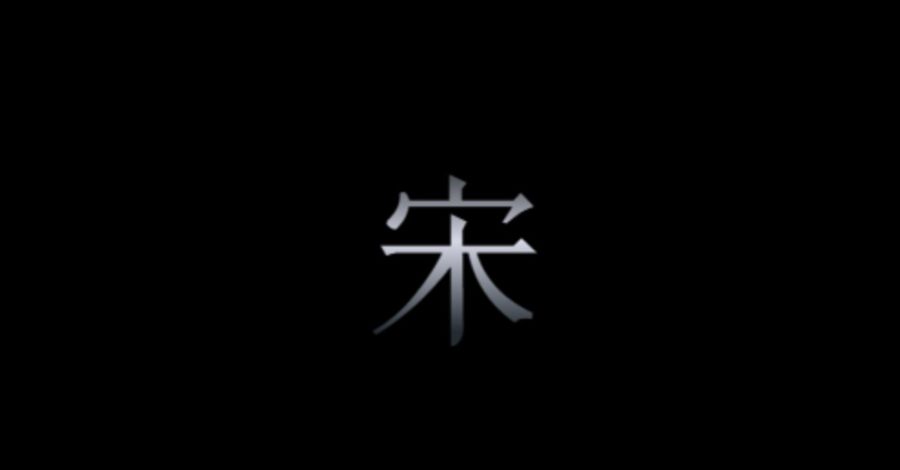
中国汉字及书法的演变大致是这样的一个过程:甲骨文、金文、大篆、小篆、隶书、草书、楷书至仿宋体、宋体字,这一过程体现了人类追求简约明朗、均衡对称、整齐统一的、程式化的总体趋向。
公元前221年,秦始皇建立了中国历史上第一个统一的中央集权制国家,随即采纳丞相李斯“书同文” 的建议,改大篆为小篆。这该是秦始皇最为智慧的一举,因为通过武力只是在地域上统一了中国,而“书同文”的统一,实是在文化上统一了中华民族,使得中央帝国在秦以后,无论战争不断、异族统治、分分合合,都只是朝代更迭而已,最后都是在汉字的伟大旗帜下繁衍、发展、壮大。到了汉代,中央集权制得到了进一步的发展和加强。这时小篆又逐渐简化演变成为隶书,史称“隶变”。在这一变化中,汉字的书写工具起了决定性的作用,毛笔的书写方式对篆书进行了方正平直化的变革,使图画性质的汉字转向抽象化,并初步形成了汉字的笔画及结构特征。独特的书写工具也成就了中国书法,柔软而富有弹性的毛笔,能随意地弯曲扭动,潇洒自如地表现出各种粗细、大小、曲直、刚柔的线条变化,更能把书者的情感赋予其中。这种“软笔”可横、可竖、可点、可捺,形成了中国书法特有的形式风格和文化特征。书者的技艺到一种高度时,毛笔在手,字已非字,点、画、线条随心书写,千变万化,以至所书之字似有生命的境界。从汉以后,中国书法稳步发展,到唐代正楷字体已达到程式化的顶峰,也为雕版印刷做好了准备。顶峰面临的是什么?是下坡,还是重新开始?唐楷成了宋体字的起始点。楷,模范也,因此,楷书顺理成章地成了中国雕版印刷字的楷模。
雕版印刷术是我国的四大发明之一,其历史可上溯至隋唐。早期雕版印刷刻写的字体,常由书法家撰写楷书后由刻工们直接反拓后临刻。刻工们对书法家十分敬重,所刻字体都尽可能地保存了书法的特点,因而有着浓厚的书法味道。这种字就是我们今天所说的“仿宋体”,也是“宋体字”前身。因此,宋体字的演变过程是通过雕版印刷技术,从书法正楷到仿宋体,再到宋体的。但为什么产生于唐宋先于宋体字的仿宋体,会叫仿宋呢?原来,这是在我国进入铅活字印刷时的事情。1916年,我国著名的书法家、篆刻家丁辅之和丁善之两兄弟参考北宋古刻善本仿写制作了仿宋体字,当时命名为“聚珍仿宋”。
由于社会对书籍需求的增长,刻工又必须更快、更多、更好地完成任务。因此,他们直接对唐代三大书法家的楷书进行改造加工,在用最少刀工的条件下,刻写出楷书的特征,这就形成了我们今天所说的宋体字。宋体字产生于唐宋,但成熟于明,所以在东邻日本称之为“明朝体”。可以说,宋体字是与中国书法一脉相承的,是对中国书法楷书的终端释义。宋体字在笔画上保持了中国书法的特点,它对书法运笔进行了高度的艺术化概括,并非常巧妙地、合理地把中国书法楷书的特征用刻刀及传统印刷术的形式反映出来,得到了中华民族的认同。
在品味和设计宋体字时,对中国书法和木版刀味、雕版印刷痕迹韵味的追求是十分重要的。如果没有这种感觉,那只是美术字而已,现在的圆体、综艺体就根本没有传统书法的味道。
今天,版本学家对宋体字下的定义是:“横平竖直,横细竖粗,起落笔有棱有角,字形方正,笔画硬挺。”起落笔的棱角,是宋体字一大特征,是雕版刻工们在长期的刻写过程中对唐楷笔画归纳化处理后形成特有的装饰化特征,是刻刀留下的韵味,它既保留了楷体的本质特点,又比唐楷更加方正有力。这种刀刻的痕迹在传统印刷的过程中,因印墨和中国纸张的因素,再加上压力,使得最后印制的效果,其字的棱角又稍稍圆润浑厚起来,十分耐看。因此,学书法要上溯秦汉,而设计宋体字却要直追唐楷和宋明的雕版印刷味、刻刀味,这是宋体字的源头。
在有形的中国文化中,千百年来一直在使用的首推宋体字。宋体字的形态特征和文化特征也在无形之中影响了一代又一代的中国人。中国人从小在一个个小方格、大方格本中练习写字,老师要求要根据字体的笔画顺序把字端正、均匀、居中地写在方格内,不能偏格也不能逾越方格,要在这方格内经营笔画的位置,相互谦让,安排好每笔每画,利用好每个小空间。正是这些因素,养成了中国人做事规矩守信又善于经营位置的国民性格。
如今学术界把宋体字排除在中国书法之外,当成美术字,这是非常不对的,书法可将金石纳入,为什么不可以将雕版纳入。因此,要正本清源地指出:宋体字不是美术字,它是正本汉字。美术字是对正本汉字进行美化、装饰、加工、设计后的各种字体,按照前述对宋体字的溯源研究,其正确的定位应该是:
楷书——仿宋字(早期的宋体字,现硬笔字的正字)——宋体字(成熟期的宋体字,印刷体的正字)——各种美术字
此外,仿宋体和宋体在笔画上是有所区别的。宋体字因刻刀刻写的关系,某些字和笔画是特别设计的,因而不适合用硬笔书写。在日本仿宋体被称之为教科书体,这种定位对初学汉字的小学生是非常有利的。所以笔者在这里建议,我国的小学生字典在宋体字旁最好同时标注仿宋体。
目前我们在宋体字的研究方面明显落后于港台和日本,这其中有结构的问题,更有字体神韵的问题。笔画的造型及字体的结构有没有中国书法的精神特质,有没有雕版刀刻的痕迹和传统印刷的趣味,是其关键所在。
20世纪60年代,我国的宋体字曾出现过一个高峰,其代表字体之一为上海制模一厂为《毛泽东选集》专门设计的宋二体。当时这是头等的政治任务,国家非常重视,倾力为之。但今天,宋体字的设计早已商业化,字体的研究都是由民间企业去完成。由于在文化上没有宏观的战略思想,加上文革时期的文化断层和今天的专业设计人员不屑于字体设计的工作,所以,现在的宋体字不免缺乏中国传统文化的精神内涵,在字体的使用上也是盲目跟风。很多需要用宋体字来表现中国文化端庄典雅、舒展大气的地方,却用了当下所谓时髦的字体,如政府的牌匾、信函;再如我国某国酒的设计,其品牌字体根本没有中国传统文化的韵味,更没有中国酒文化的味道,连酒厂的标准字居然也只是采用了综艺体。最近,香港地区发行的新10元纸币的设计用的是圆体,拿在手中花花哨哨,完全没有权威感,与原有的百元、千元纸钞的设计相去甚远。
要改变当下我国宋体字的发展状况,应该做到:
1. 明确宋体字不是美术字,这对于中国文化的发展有着重要的意义,这样才能把宋体字的研究推向一个新的高度。
2. 应该把宋体字纳入国家文化发展的总体战略中去,以国家的行为去研究它。在此笔者建议成立“国家字体研究所”专门对此进行研究。例如在法国就有专门从事字体研究的机构——“法国国家字体研究室”。
3. 给予宋体字明确的地位。如“国家字体研究所”推出的宋体字,可称为“国宋”。可以以序号命名“国宋1号”、“国宋2号”,或以风格命名“国宋典雅”、“国宋方正”。
千百年来,外来文化一直冲击着中国传统文化,虽然中国文化有着巨大的包容性,但也应警惕在这包容的同时会不知不觉地失去许多自己应固守的东西。今天我们已很少着唐装,也不拱手抱拳行礼了,而相邻的日本却仍旧鞠躬行礼,仍旧保留着和服。今日,我们的国家日益昌盛,正是中华民族文化发展的大好时机,经济要发展,文化更要发展,作为中国文化的代表——宋体字更要常新、常靓,并引领汉字文化的流向。